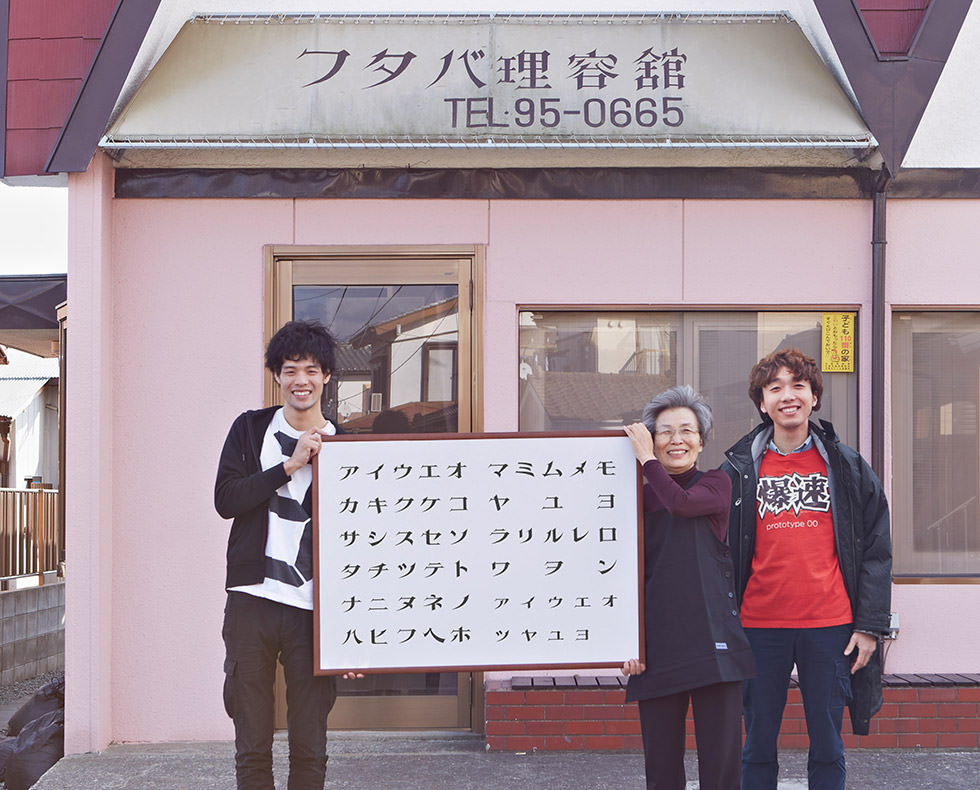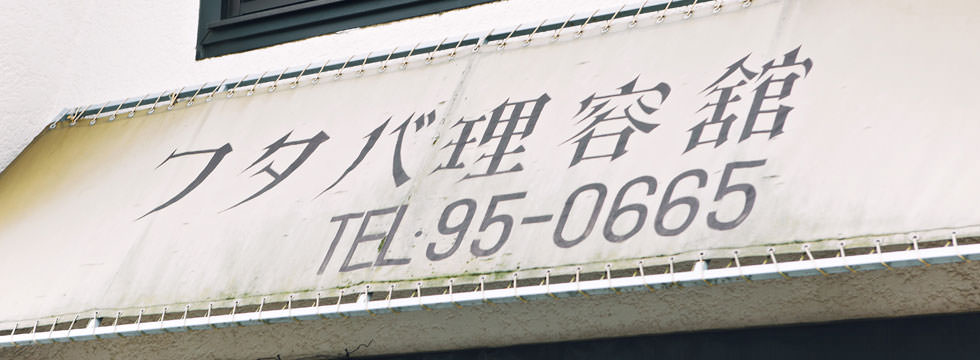
シャープで、真面目な雰囲気。理髪店であるので、髪のカットにおける鋭さ・正確さを表しているのだろう。細部に見られる処理がレトロでお洒落。
「フタバ理容館」は1969年に現店主の藤山さんがひとりで開業した。屋号は店舗のある双葉町にちなんでつけたそう。中学校を卒業した15歳の頃から、東京に出て理容師の修行をし、28歳のときに独立した初めて石巻の街に来たという。「あたしなんぼだと思う?73なんだよ。カラ元気だっちゃ。でも、膝痛い、腰痛い、っていうわけでないからね、んだよ、楽しいね。ほんと、この仕事して良かったなって思うよ。だってお客さんからきてくれるもん。「はい、いらっしゃ〜い!」って(呼び込まなきゃならない)んでないんだもん。お客さんの方から来てくれるんでもう本当に良い仕事だっちゃ。仕入れて作ってかないといけねってのでないもん。手さ職つけて、そんでお金貰えるんだもの。これほど良い仕事は無いと思うよ。」そう、遠山さんは楽しそうに語ってくれた。